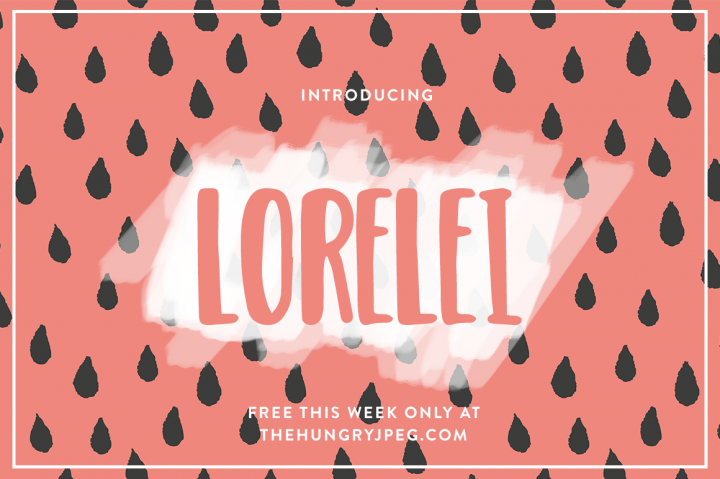
Aqui está uma breve descrição para a página de download da fonte ‘Lorelei Font’: A fonte Lorelei é um belo exemplo de design digital que evoca momentos autênticos e humanos do mundo das letras. Desenhada pelo designer Hamilton, esta brush font retrata uma escrita delicada e elegante que parece ter saído direto da mão de um artesão de calligrafia. Ideal para qualquer projeto visual que busque transmitir um toque delicado ou uma atmosfera romântica e contemporânea, Lorelei traz a conveniente flexibilidade de ser usada em diversos formatos — seja em logotipos, publicações digitais ou até mesmo designs gráficos. Seja você designer gráfico, blogueiro de design ou qualquer criador que esteja buscando uma fonte que transmita um ar elegante e sofisticado, Lorelei é certamente um recurso imprescindível. Ao adquirir Lorelei Font, você recebe não apenas a conveniente ferramenta para expressar suas ideias visualmente, mas também uma conexão direta com o design artesanal que inspirou seu conceito. Com esse design elegante e autêntico, Lorelei é certamente um recurso indispensável tanto para os iniciantes quanto para profissionais do design que desejam adicionar sofisticação a seus projetos.